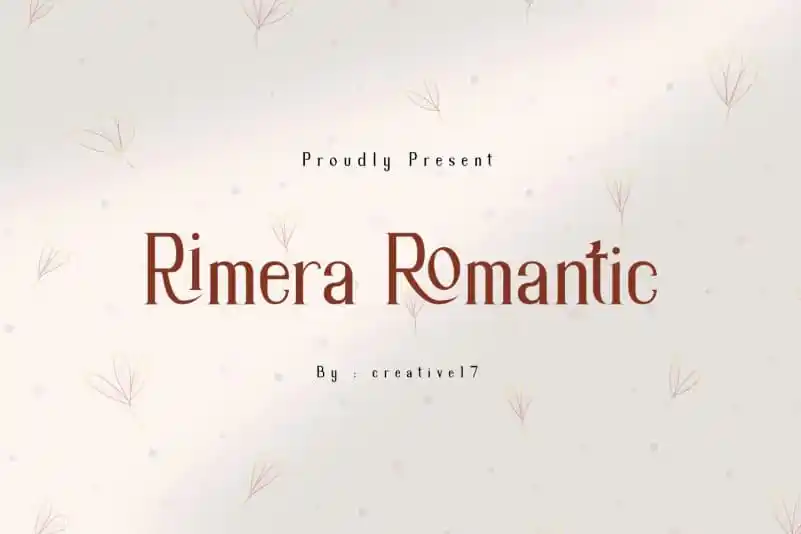
Rimera Romantic Serif Font – Download Grátis
A Rimera Romantic Serif é uma fonte serif clássica criada por Irfan Hidayat, ricas em estilo e caracterizada pela sua leve contraste minimalista. Esta fonte se destaca não apenas por sua aparência elegante e sofisticada, mas também pelas suas muitas possibilidades de uso. É perfeitamente adequada para projetos que requerem um tom de design mais formal, como cartões de negócios, convites de casamento, logotipos de letras grandes, designs de marca e títulos de panfletos. Além disso, a Rimera Romantic Serif oferece suporte linguístico multilíngue, garantindo uma experiência intuitiva para designers trabalhando em projetos que exigem múltiplas línguas ao mesmo tempo. Com sua design profissional e estilo romântico clássico, esta fonte é perfeita para aqueles buscando um toque de sofisticação e elegância em seus projetos gráficos. O equilíbrio entre as linhas finas e grossas da fonte criam uma aparência harmoniosa e envolvente que se adapta a uma variedade de contextos, desde design empresarial até criações artísticas mais românticas. Para designers entusiasmados com o universo da tipografia e do design gráfico, a Rimera Romantic Serif é uma escolha inteligente para quem busca qualidade e funcionalidade em um único produto.